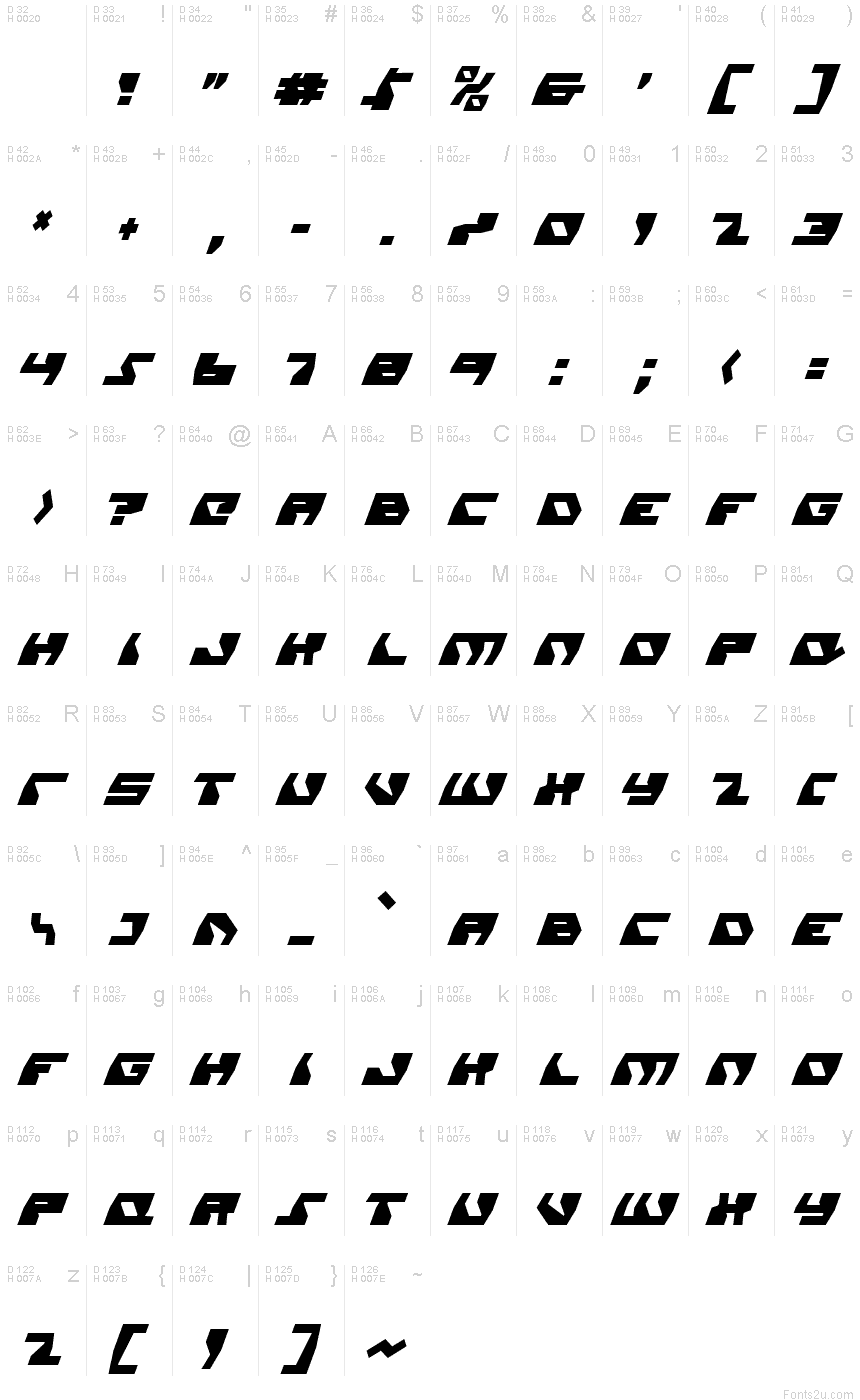
Daedalus Condensed Italic od Iconian Fonts to darmowy, futurystyczny krój pisma typu display, składający się wyłącznie z wielkich liter i utrzymany w klimacie twardej fantastyki naukowej. Litery są wycięte w ostre, pochylone kliny i połamane paski, co nadaje krojowi szybki, mechaniczny rytm, bardziej przypominający oznaczenia na statkach kosmicznych i tytuły z automatów do gier niż zwykłe liternictwo display.
Naturalnie pasuje do logo gier, nagłówków plakatów, okładek albumów, brandingu technologicznego i plansz tytułowych, gdzie krótkie słowa potrzebują syntetycznego, napędzającego charakteru. Jako darmowy font, sprawdza się również w monogramach i liniach okładkowych, ponieważ wąskie, ukośne wielkie litery łączą się w zwarte, graficzne formy.
Daedalus Condensed
Condensed Italic
Dan Zadorozny